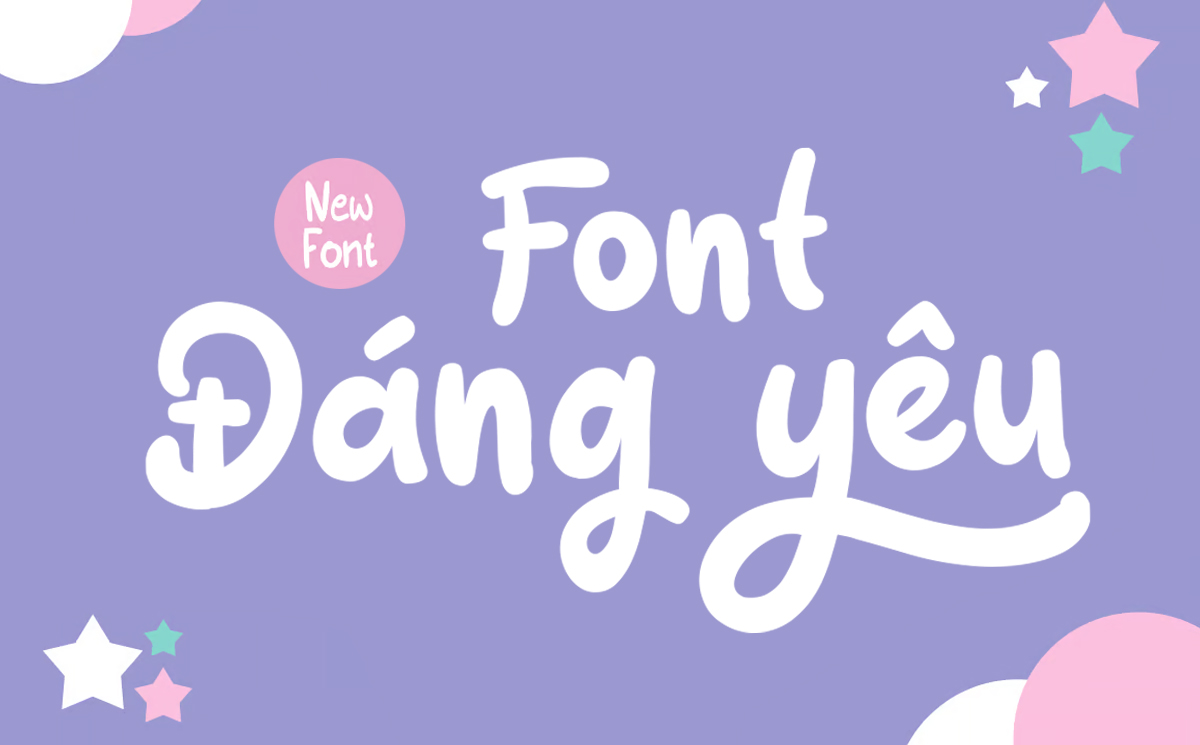
Font chữ cute đáng yêu Việt hóa SVN-Claytonia
Trong thế giới thiết kế đồ họa hiện đại, việc lựa chọn một phông chữ phù hợp không chỉ giúp truyền tải thông điệp rõ ràng mà còn tạo nên cảm xúc đặc biệt cho người xem. Font chữ cute đáng yêu Việt hóa SVN-Claytonia chính là giải pháp hoàn hảo dành cho những ai đang tìm kiếm sự ngọt ngào, gần gũi và đầy tính sáng tạo cho các sản phẩm truyền thông của mình. Bộ font này sở hữu những đường nét viết tay tự nhiên, ngộ nghĩnh cùng khả năng hiển thị tiếng Việt mượt mà, giúp các bản thiết kế trở nên sinh động và ấn tượng hơn bao giờ hết.
Font Chữ Cute Đáng Yêu Việt Hóa SVN-Claytonia – Giải Pháp Thiết Kế Ấn Tượng Và Độc Đáo
Nếu bạn đã quá quen thuộc với các phông chữ chuẩn mực, cứng cáp như Sans-Serif hay Serif truyền thống, thì SVN-Claytonia sẽ mang đến một làn gió mới đầy phá cách. Phông chữ này thuộc nhóm handwriting (chữ viết tay) với phong cách thiết kế tự do, ngẫu hứng nhưng vẫn đảm bảo tính cân đối và dễ đọc. Quá trình Việt hóa chỉn chu từ đội ngũ SVN giúp font chữ xử lý hoàn hảo toàn bộ hệ thống dấu câu tiếng Việt, xóa tan nỗi lo lỗi font hay lệch ký tự khi gõ các đoạn văn bản phức tạp.
Dù bạn là một designer chuyên nghiệp, một content creator hay một chủ shop online đang tự tay thiết kế hình ảnh quảng cáo, font SVN-Claytonia chắc chắn sẽ là một công cụ trợ thủ đắc lực không thể thiếu trong bộ sưu tập tài nguyên của bạn.
1. Đường Nét Mềm Mại, Tròn Trịa Mang Phong Cách Hand-Drawn Trẻ Trung
Điểm đặc trưng nổi bật nhất của SVN-Claytonia chính là nét vẽ mang đậm hơi hướng thủ công (hand-drawn). Mỗi nét chữ đều gợi lên sự mộc mạc, đáng yêu giống như nét chữ viết tay của những cuốn nhật ký hay bưu thiếp kỷ niệm. Cấu trúc chữ tròn trịa, tỷ lệ giữa các ký tự được sắp xếp một cách tự nhiên giúp tạo cảm giác thân thiện, kéo gần khoảng cách giữa thương hiệu và khách hàng.
Sự kết hợp giữa nét thanh nét đậm vừa phải giúp phông chữ không bị thô cứng mà luôn giữ được sự uyển chuyển. Khi áp dụng vào các ấn phẩm truyền thông, nét dễ thương của SVN-Claytonia có khả năng thu hút thị giác của người xem ngay từ cái nhìn đầu tiên, đặc biệt là nhóm đối tượng khách hàng trẻ tuổi, học sinh, sinh viên hoặc phái đẹp.
2. Bộ Ký Tự Việt Hóa Chuẩn Từng Nét, Không Lỗi Font Tiếng Việt
Một trong những vấn đề lớn nhất mà người làm thiết kế tại Việt Nam thường gặp phải khi sử dụng các bộ font nước ngoài là bị lỗi dấu (như các dấu sắc, huyền, hỏi, ngã, nặng hoặc các chữ ê, ơ, ư bị mất nét). Nhận biết được điều đó, phiên bản Việt hóa SVN-Claytonia đã được chỉnh sửa cẩn thận từng chi tiết glyphs.
Hệ thống dấu tiếng Việt được đặt đúng vị trí, tỷ lệ cân đối với thân chữ chính, đảm bảo tính thẩm mỹ cao khi gõ các cụm từ dài. Dù bạn gõ những từ có nhiều dấu phức tạp như “khuyến mãi”, “ngọt ngào”, “yêu thương” hay “ngây thơ”, văn bản vẫn hiển thị vô cùng mượt mà, chuyên nghiệp và chuẩn xác.
3. Tính Ứng Dụng Đa Dạng Trong Nhiều Lĩnh Vực Thiết Kế Chiêu Thị
Nhờ sở hữu vẻ đẹp cute và đáng yêu, SVN-Claytonia có khả năng ứng dụng vô cùng linh hoạt trong nhiều dự án thiết kế khác nhau. Bạn có thể dễ dàng bắt gặp hoặc ứng dụng bộ font này vào các ấn phẩm như:
• Thiết kế mạng xã hội: Tạo các bài đăng Facebook, Instagram, TikTok, banner quảng cáo hoặc ảnh thumbnail YouTube với phong cách nhí nhảnh, gần gũi.
• Bao bì sản phẩm & Thẻ bài: Rất thích hợp cho các sản phẩm dành cho trẻ em, mỹ phẩm thiên nhiên, tiệm bánh ngọt, trà sữa, quà tặng handmade hay thiệp mừng sinh nhật, thiệp cưới phong cách rustic.
• Thiết kế sách báo & Truyện tranh: Làm tiêu đề cho các cuốn sách thiếu nhi, bìa sổ tay, sticker trang trí trang sổ Planner/Bullet Journal.
• Typography & Quote: Biến những câu trích dẫn hay, những câu slogan ngắn thành các tác phẩm nghệ thuật chữ bắt mắt để chia sẻ lên các trang mạng xã hội.